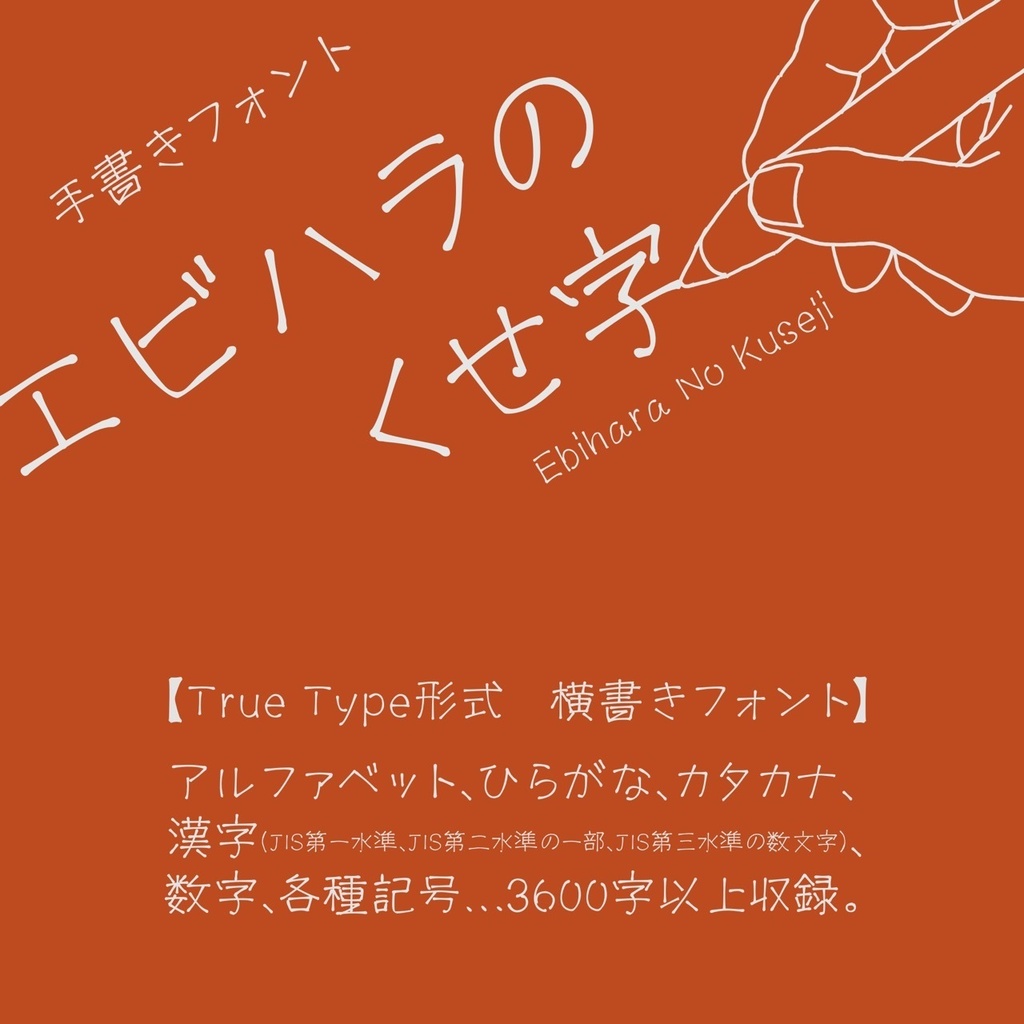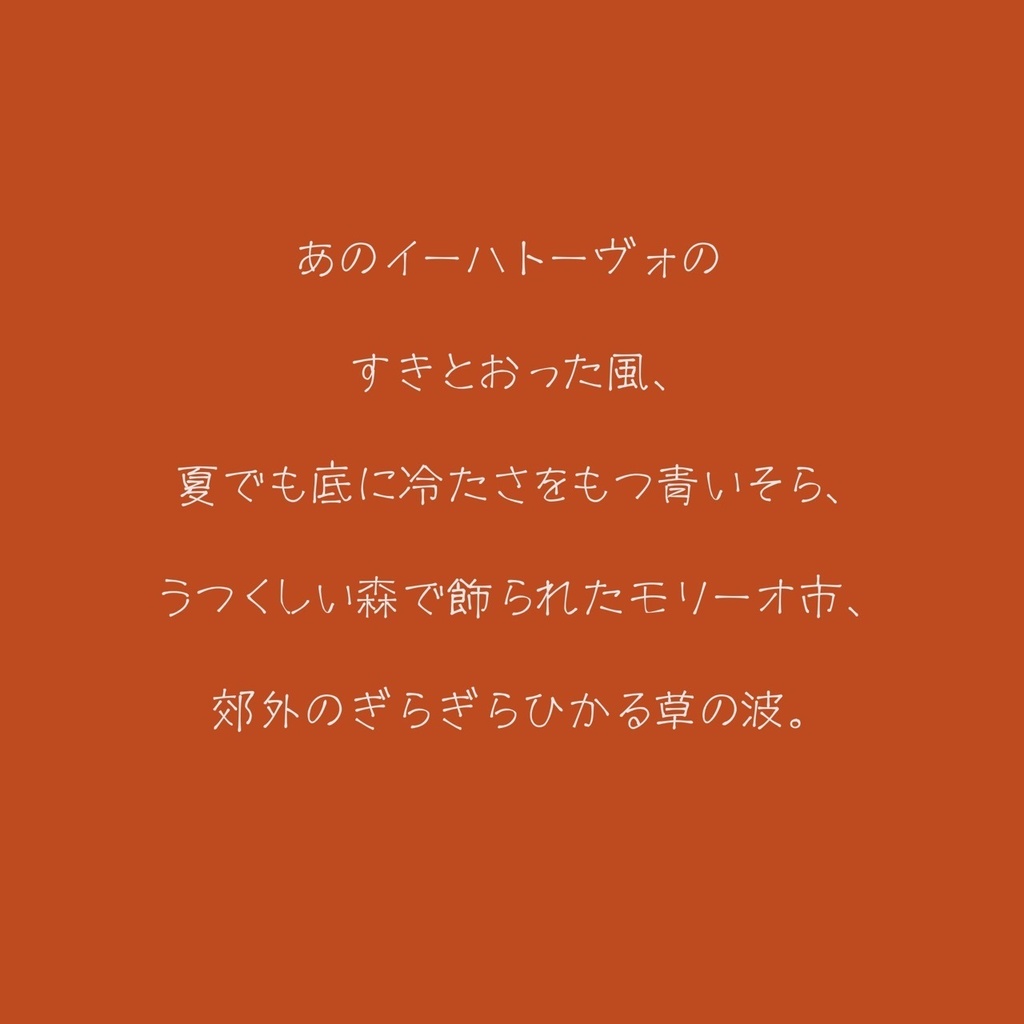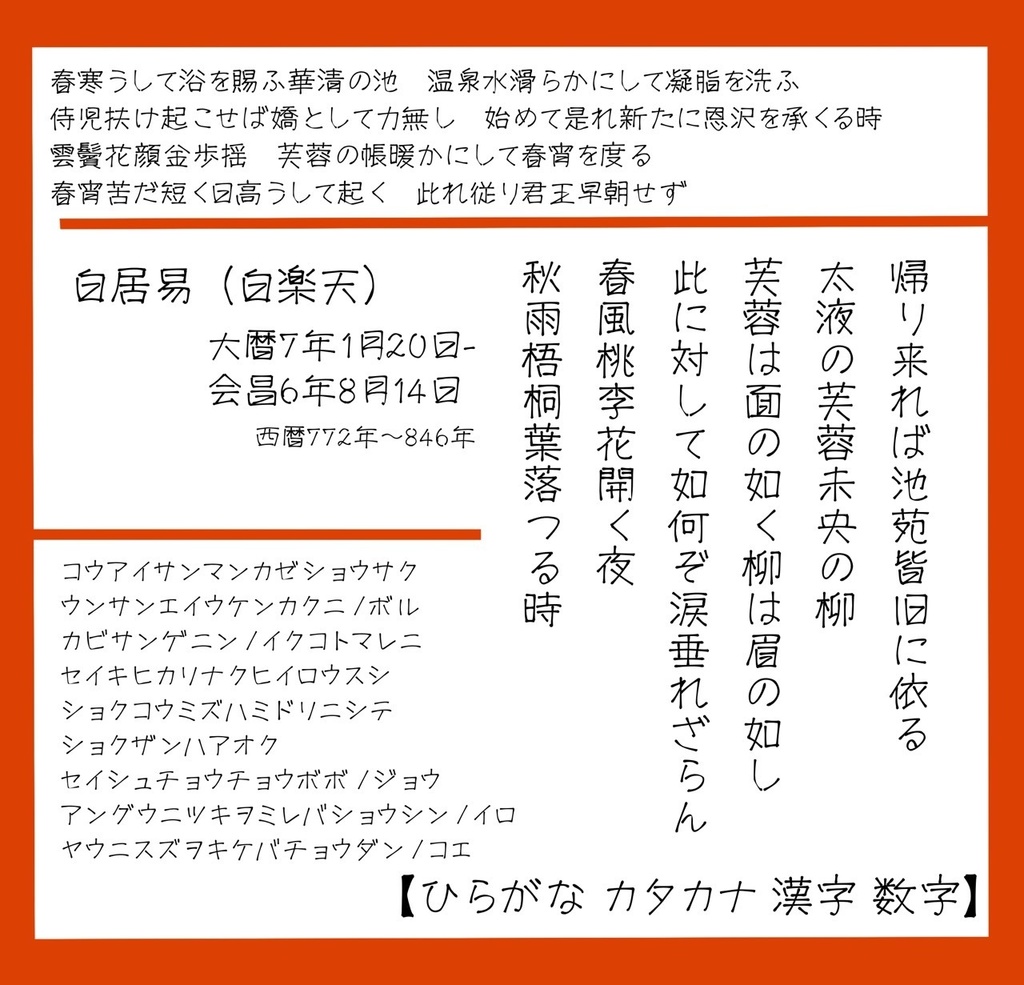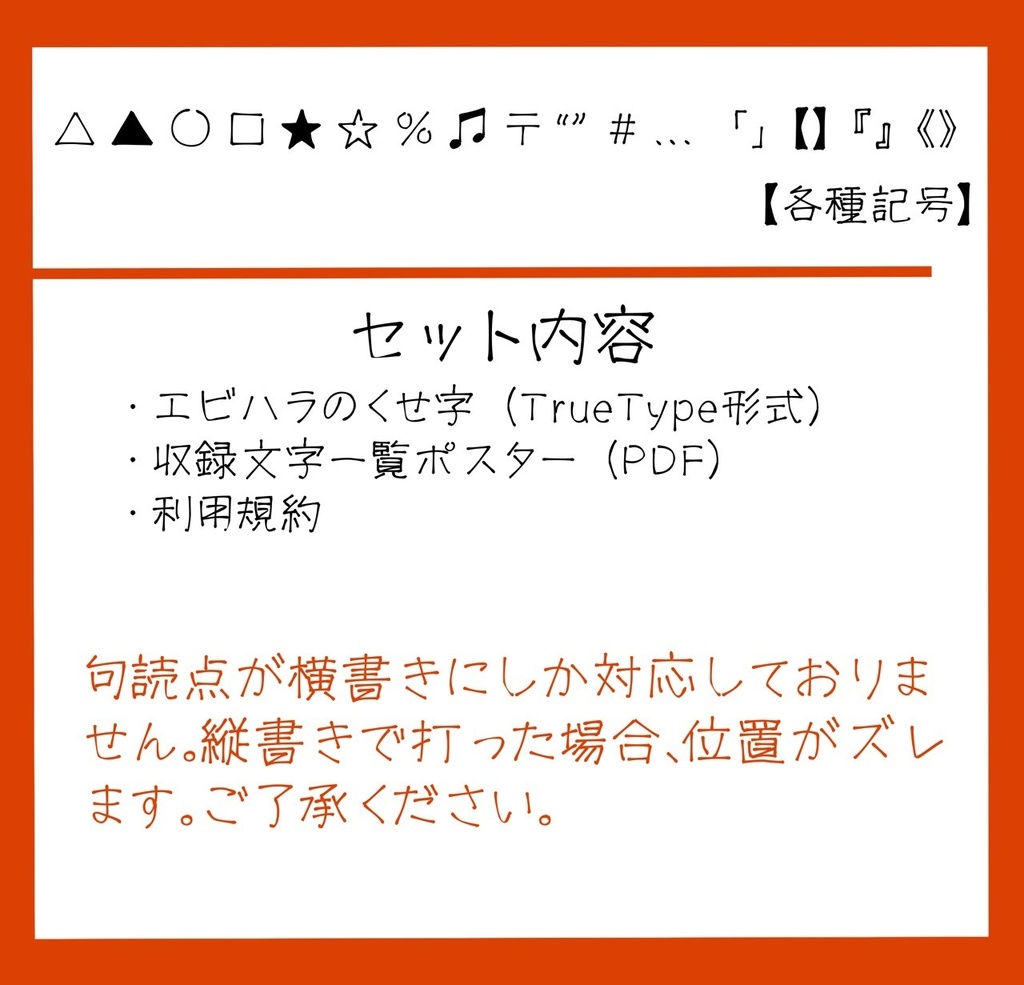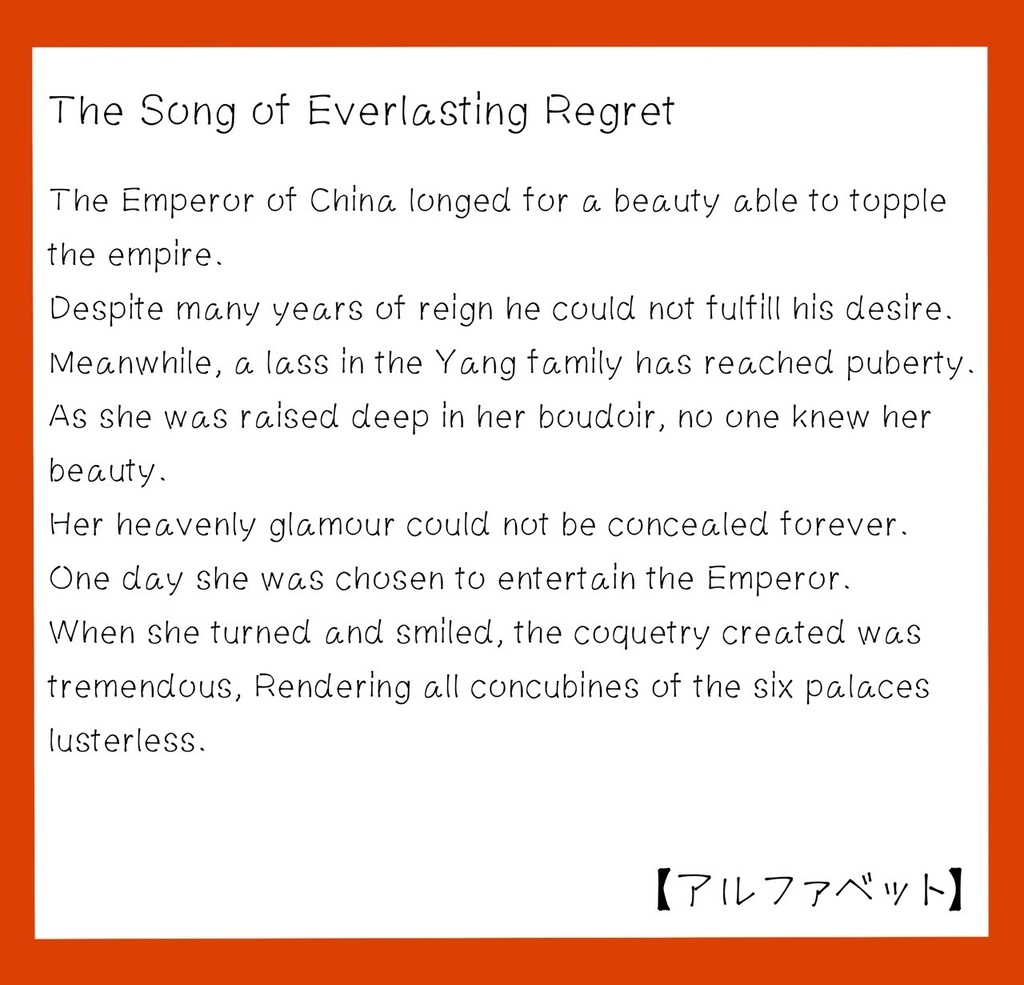
【手書きフォント】エビハラのくせ字
2026/10/15 行間やバランスなどの修正 2025/4/18 文字追加 2024/5/26 文字追加 2024/2/2 文字追加 2023/10/22 文字追加 2023/7/11 リクエスト文字追加・いくつかの既存文字の修正 2023/5/7 文字追加 2023/3/7 文字追加(3603字になりました) 2023/2/4 文字追加・不具合修正 2023/1/13 不具合修正 2022/11/27 文字追加 2022/9/23 文字追加 2022/9/14 不具合修正 2022/7/5 不具合修正 ーーーーーーーーーーーー 横書き用の手書きフォントです。 「フォントっぽい」と言われることが多い自分の字を、実際にフォントにしてみました。作成に使用したのはiPadのアプリ「iFontMaker」です。 手癖全開で書くとバランスが悪いため、普段の手書き文字をベースに、なるべく等幅になるよう心掛けて作りました。 メイリオのような幅広で大きめなフォントが好きなかたにおすすめです。ただし、ところどころ独自の癖が出ているので、サンプル画像で雰囲気をご確認ください。 無料版と投げ銭版がありますが、内容はどちらも同じです。投げ銭は、お気に召しましたら何卒、宜しくお願いします。 自分でもこのフォントを作品作りに使用しながら、都度アップデートしていこうと思っています。文字がきちんと表示されないなどの不具合が御座いましたら、お手数をおかけしますが、お知らせくださると助かります。
【収録文字】
・アルファベット ・ひらがな ・カタカナ ・漢字-JIS第一水準全文字、JIS第二水準の一部、JIS第三水準の数文字(常用漢字は全て入っています) ・数字 ・各種記号(少なめです)